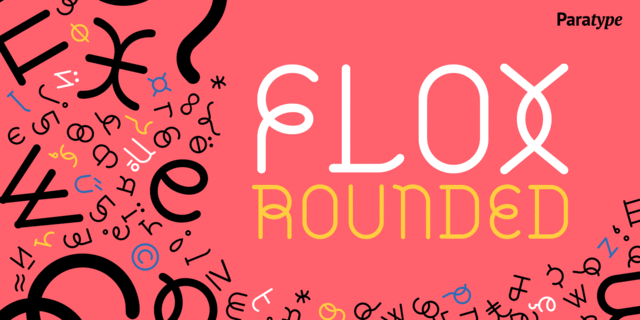
Шрифт Флекс разработан в 2000 году (дизайнер Владимир Павликов) как альтернативный, 'мягкий', вариант шрифта Флокс. В отличие от Флокса обладает круглыми окончаниями штрихов и закругленными формами большинства элементов знаков. Целью проекта было создание декоративного живого шрифта на основе геометрических форм. В 2005 году были добавлены кириллические знаки. Предназначен для применения в рекламе и акциденции. Лицензирован компанией ПараТайп в 2005 году.